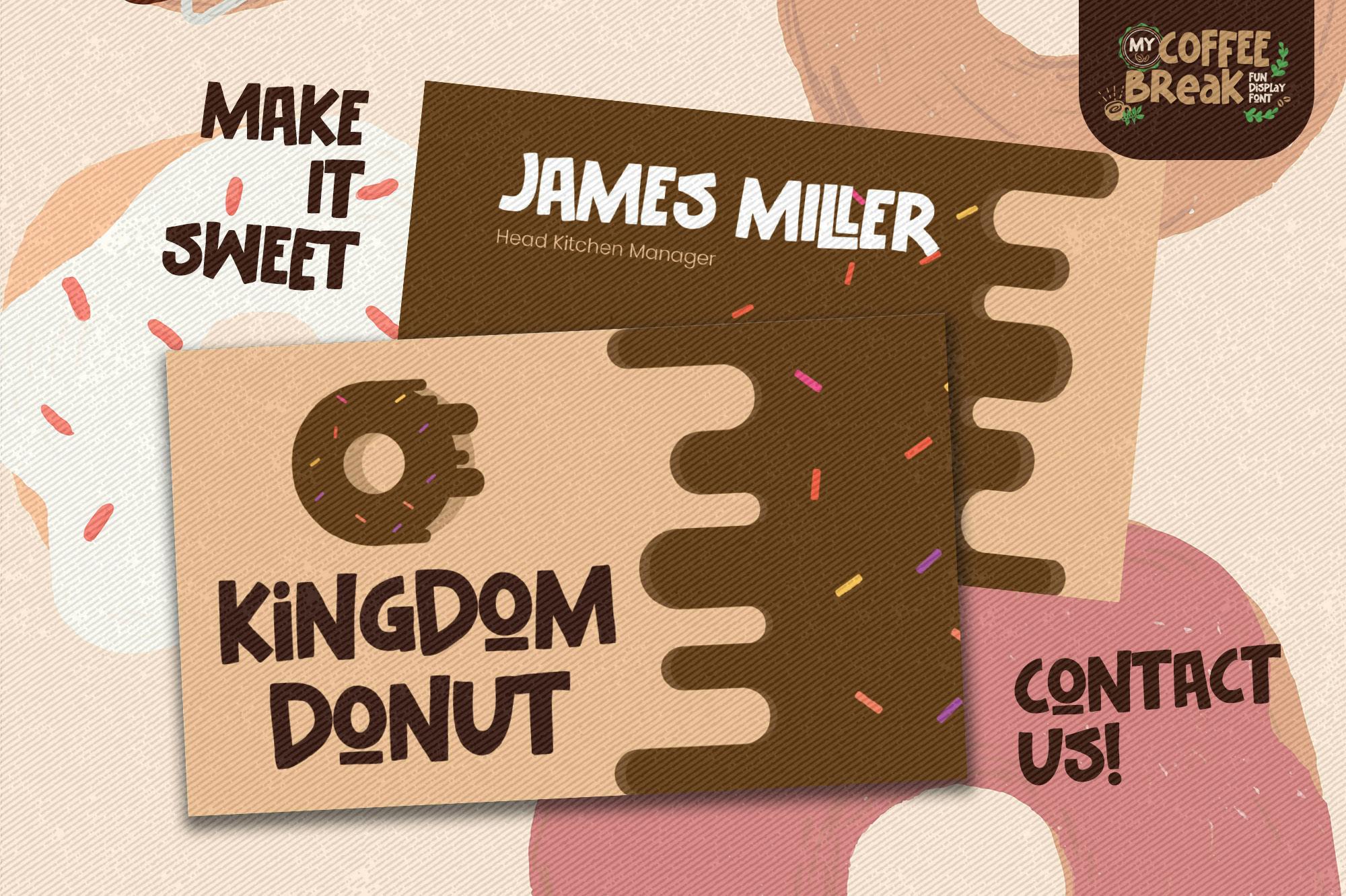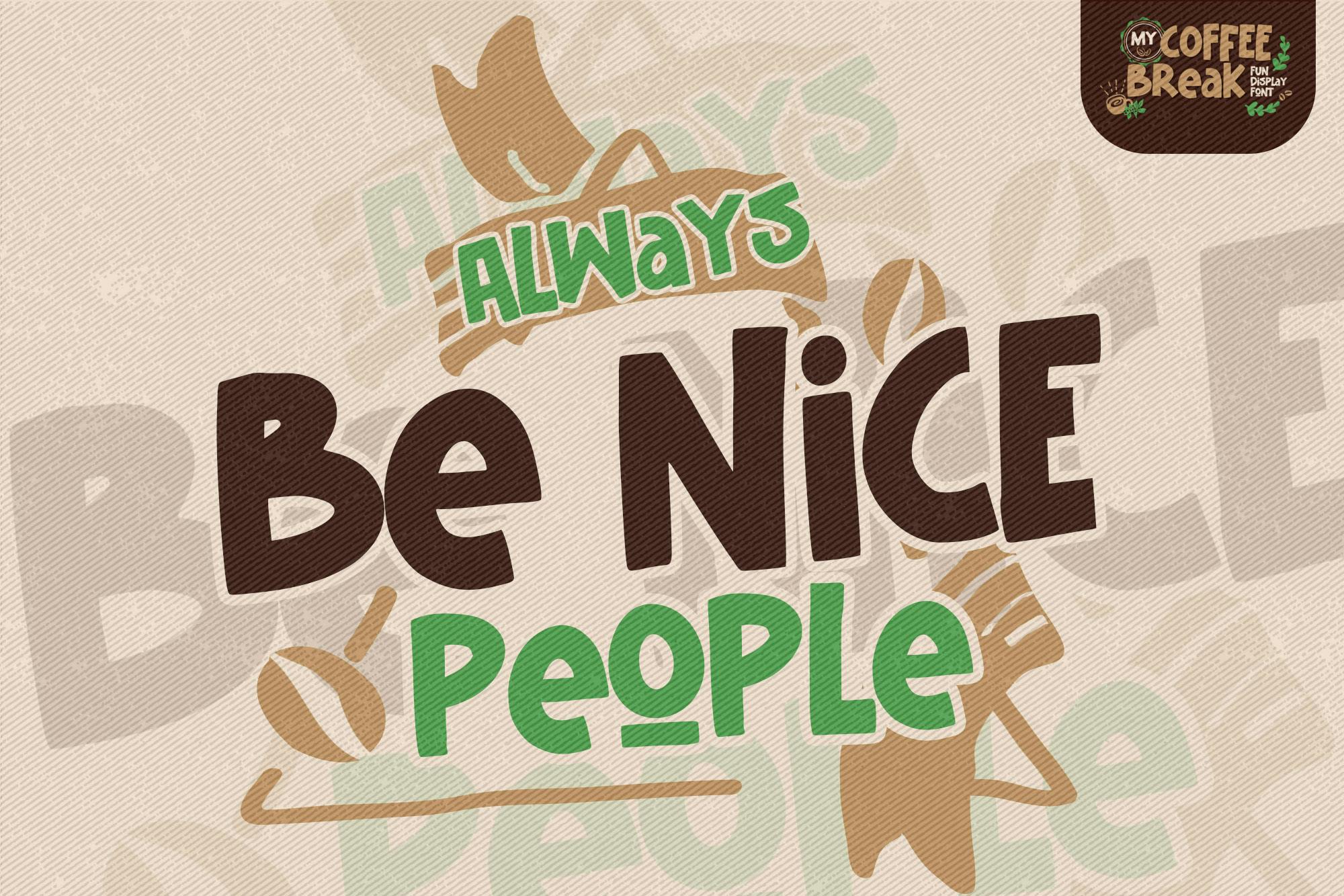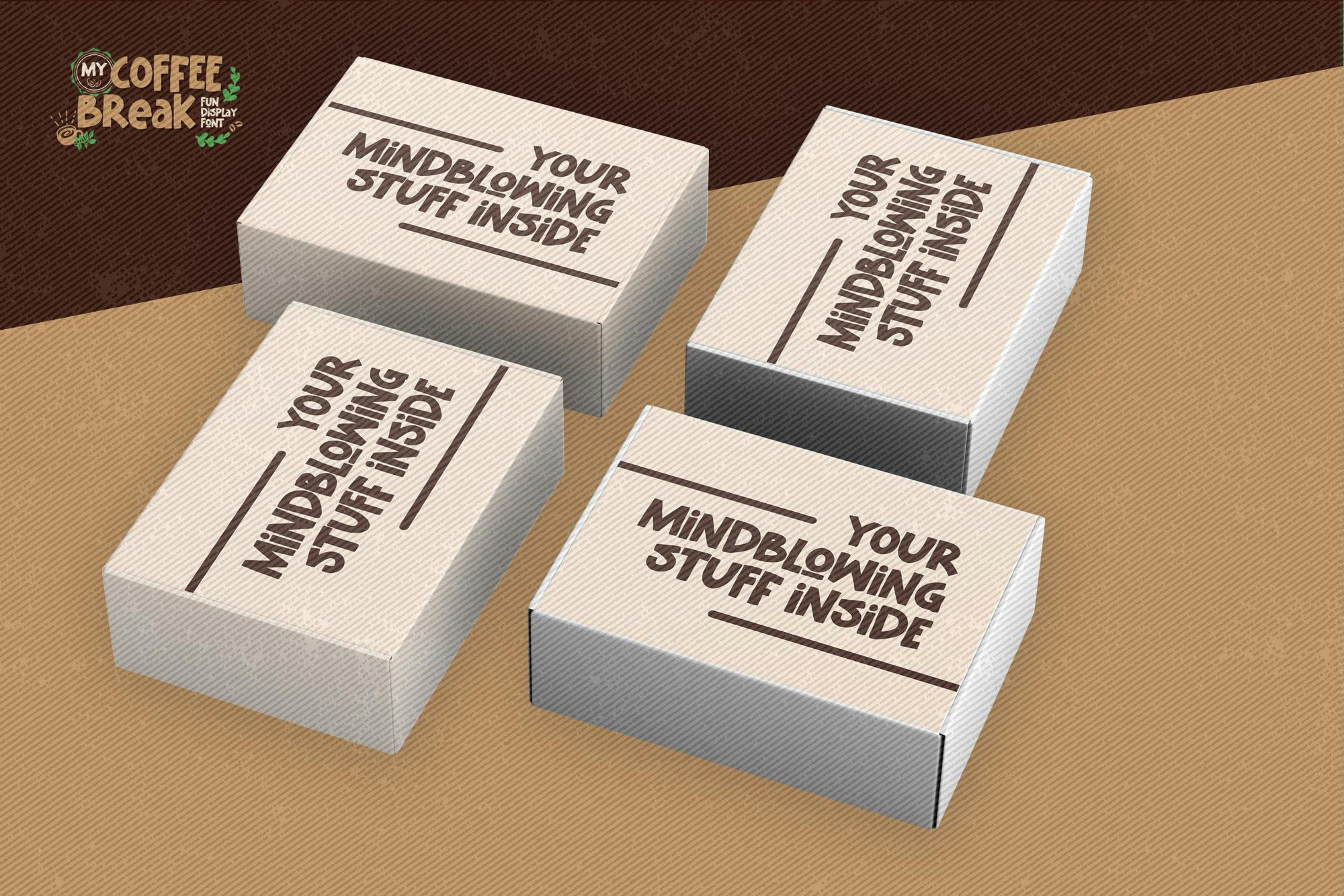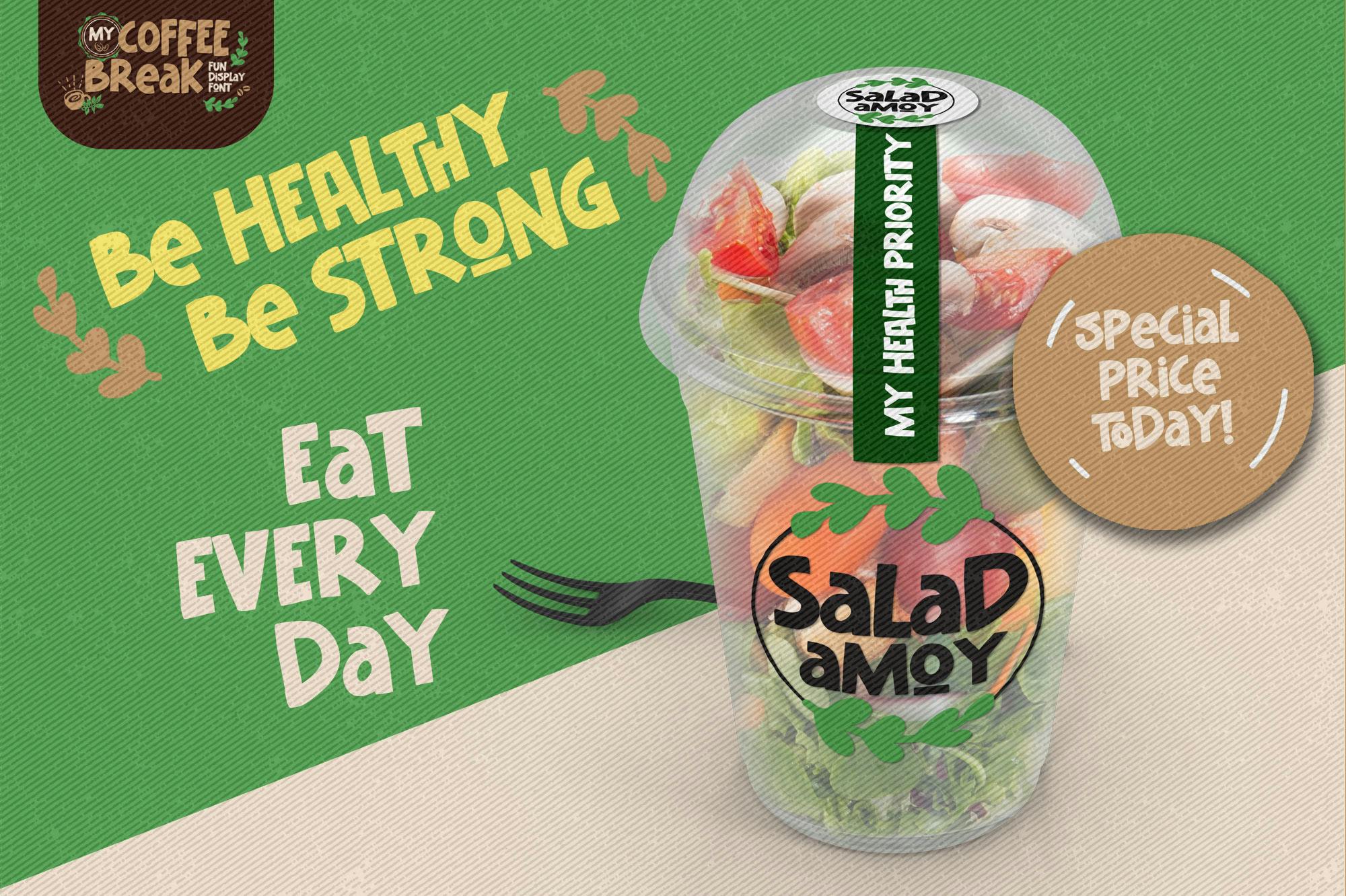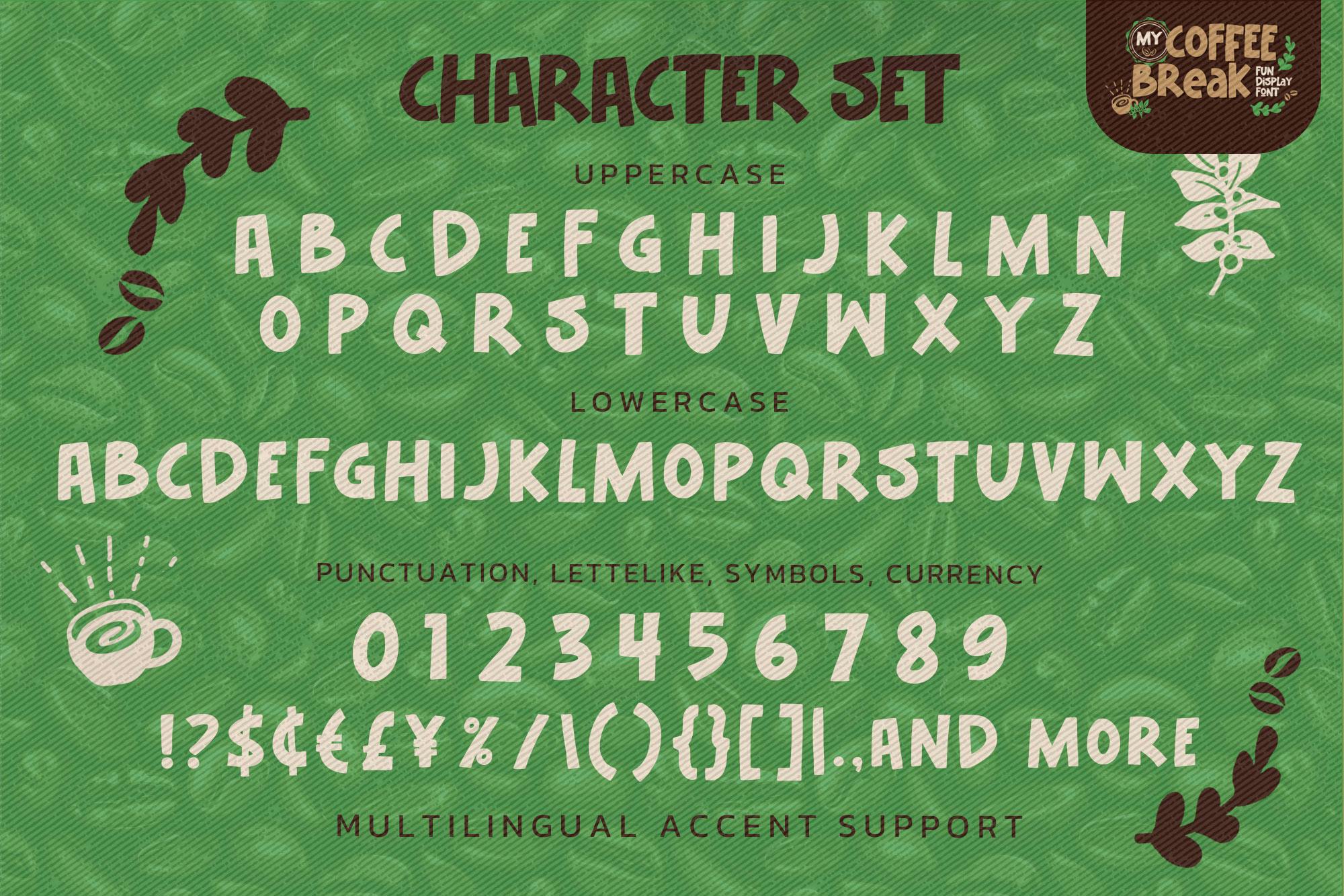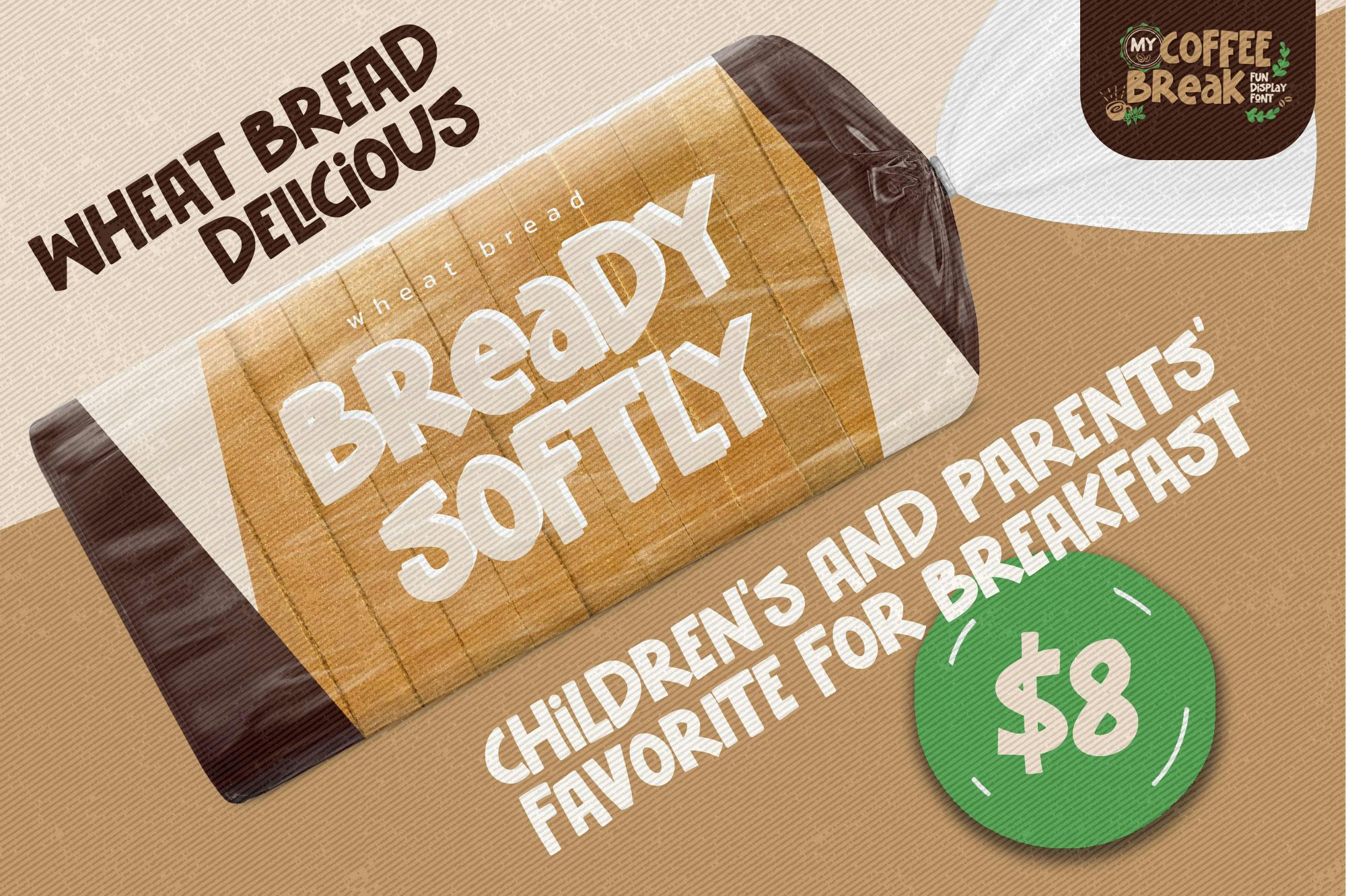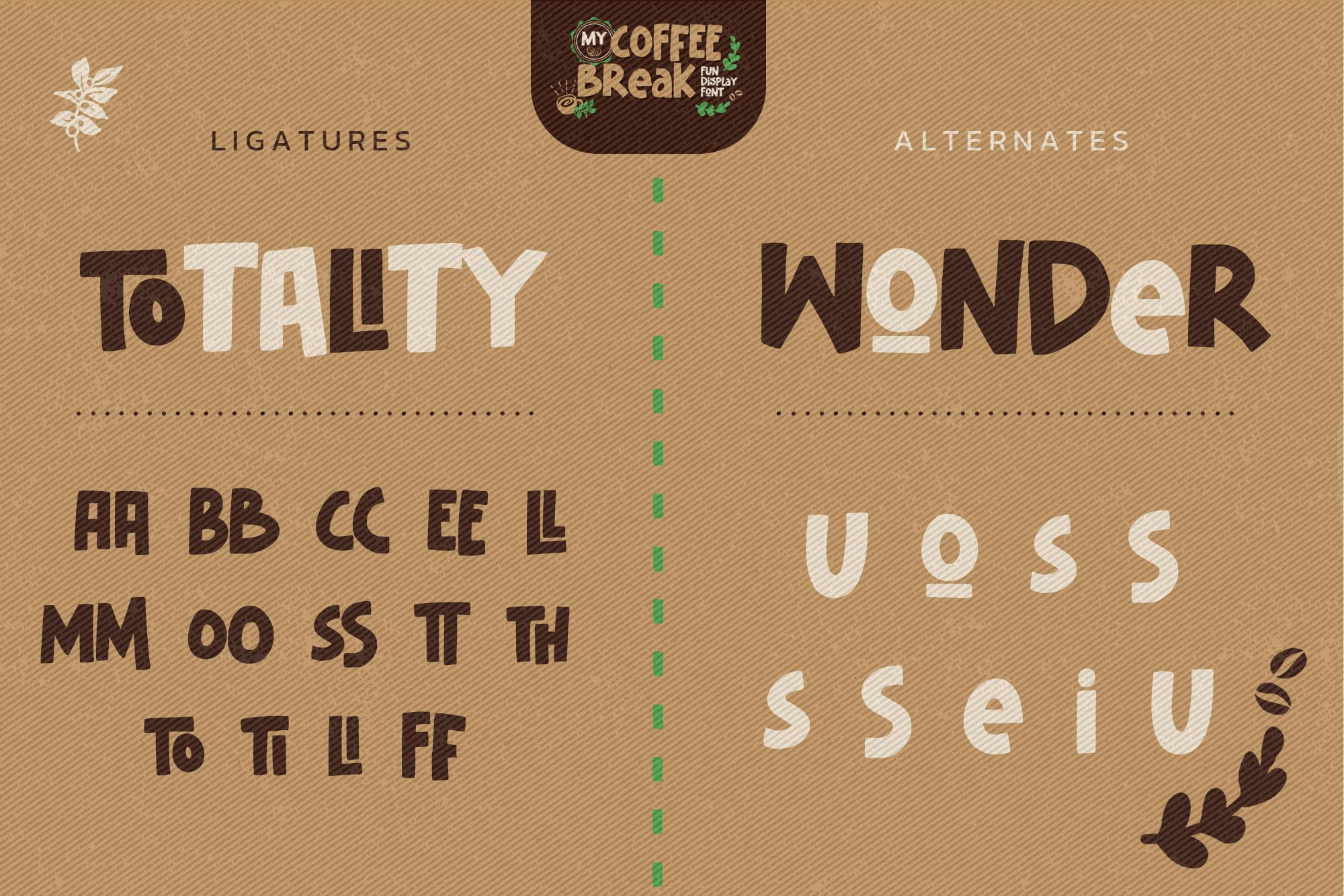
سلام به همه! ما محصول جدید خود را معرفی میکنیم: My Coffee Break، یک فونت نمایش سرگرمکننده با احساسی طبیعی. این فونت دستساز طراحی شما را با لمس زیبای طبیعی در هر جزئیات زیباتر میکند. این فونت برای هر پروژه طراحی مانند دعوتنامه، لوگو، جلد کتاب، کاردستی یا هر هدف طراحی دیگری مناسب است.
My Coffee Break الهامگرفته از سبک لوگوی غذا و ترکیب با سبک کاردستی منحصر به فرد است که نیازهای طراحی شما را برای نقلقولها، تمهای ورزشی، لوگوتایپ، ووردمارک و غیره برآورده میکند. این فونت دارای ویژگیهای متعدد اوپنتایپ و پشتیبانی از چند زبان است. این فونت کدگذاری PUA شده است، به این معنی که میتوانید به راحتی به تمام گلیفهای جادویی دسترسی پیدا کنید!
این فونت همچنین دارای ویژگیهای خاصی از جمله گلیفهای لیگاتور و گلیفهای جایگزین میباشد.